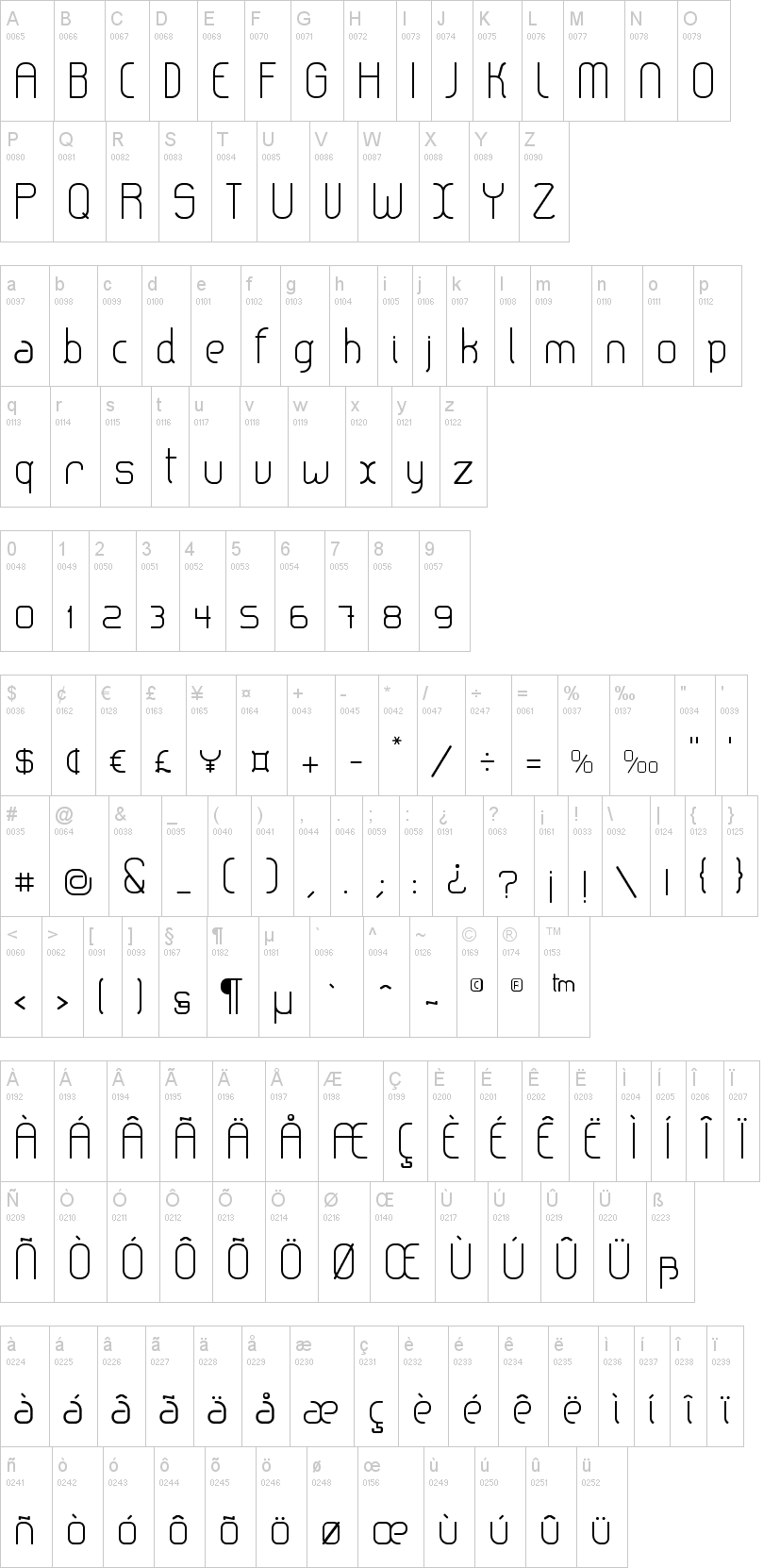
Шрифт Lerotica
Esta tipografía surge de la inspiración resultante de la creación de un logo tipográfico para una marca de relojes, está diseñada sobre cuadrícula de 100 x 100 pt. Es una tipografía sin serif y semi condensada.
This typeface comes from the inspiration arising from the creation of a typographic logo for a watch brand, is designed for grid 100 x 100 pt. It is a sans serif typeface and semi condensed.